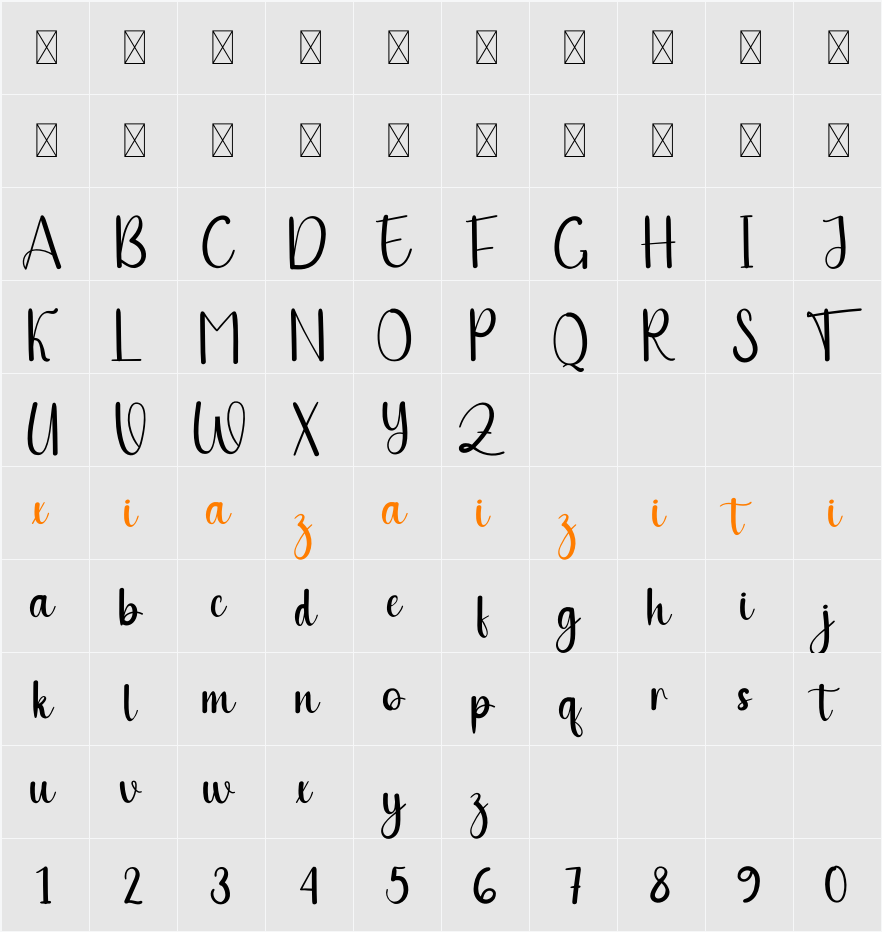
Winter Mountain
Winter Mountain,这款字体结构工整、笔画清晰,兼顾美观与易读性,适用于标题、正文、海报、包装、LOGO 等多种场景。字形优雅稳定,风格百搭耐看,适配日常排版与创意设计,让文字呈现更舒适、更具质感。Winter Mountain一笔一画,皆是细节,以均衡的比例、流畅的线条打造舒适视觉体验,字形端正大气,风格简约现代。无论是商业设计、品牌宣传还是日常排版,都能轻松驾驭,让文字更有格调与力量。Winter Mountain字体下载。